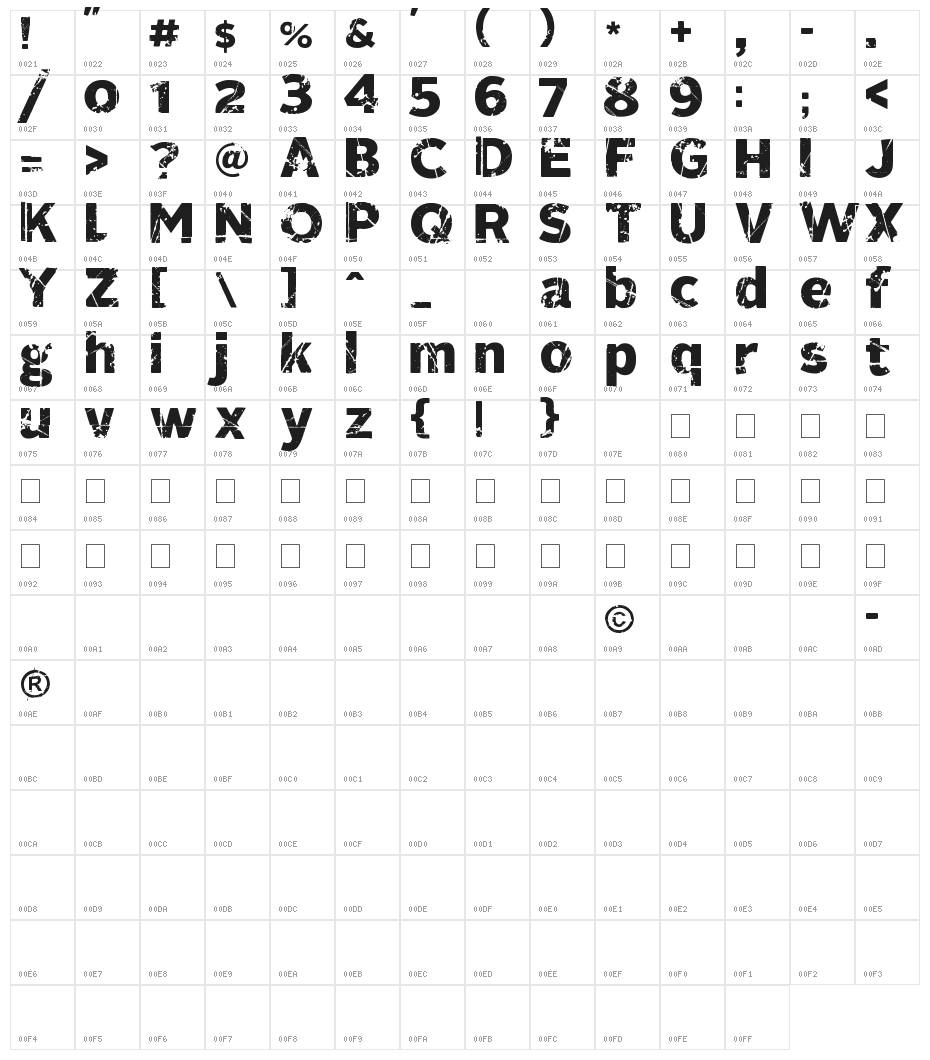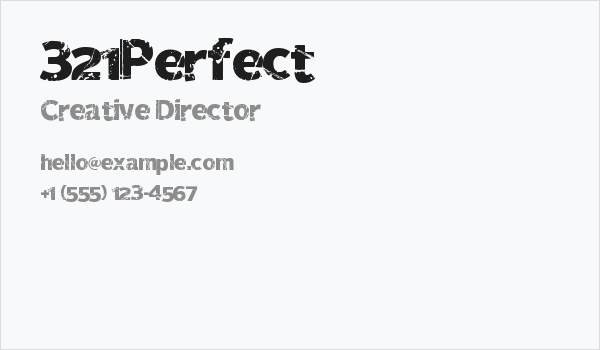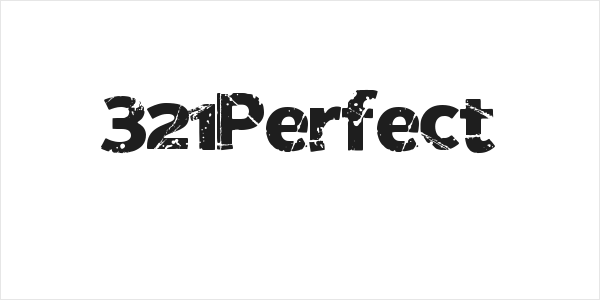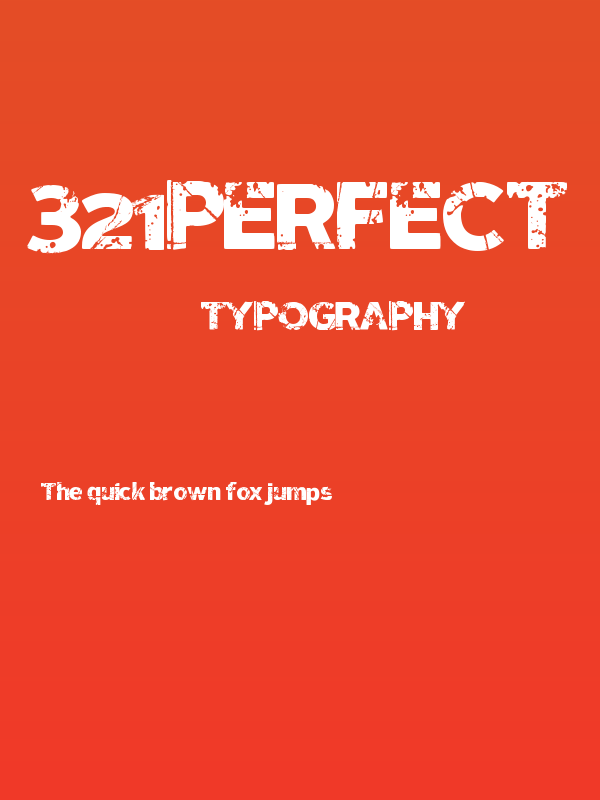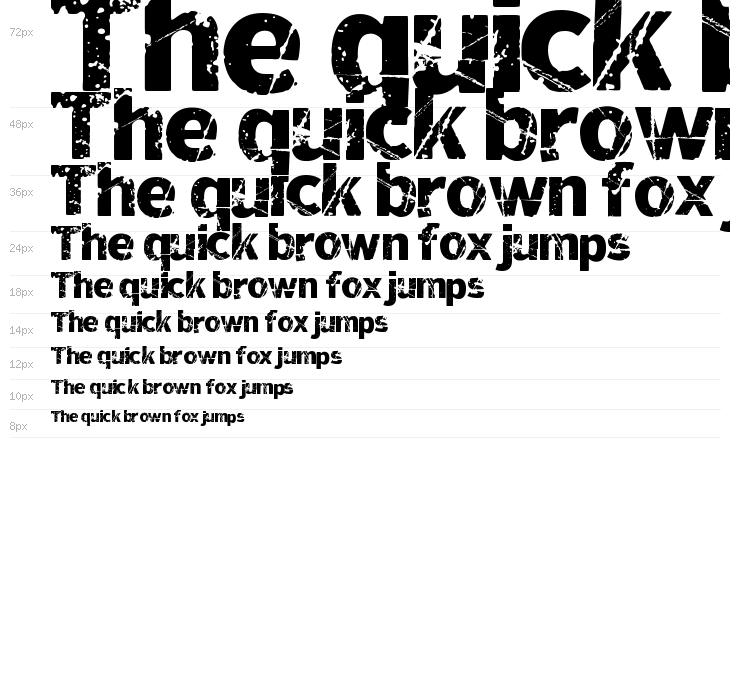
321Perfect Font
| Stile generale | Grunge, Vintage |
| Progetti proposti | Ideal for posters, album covers, branding for edgy or vintage-themed products, and any design needing a bold, textured look. |